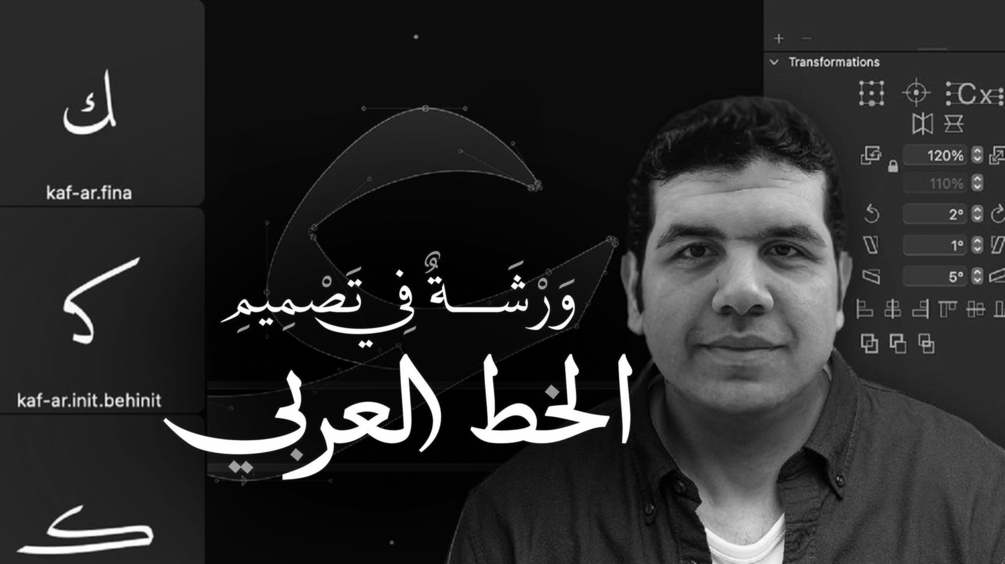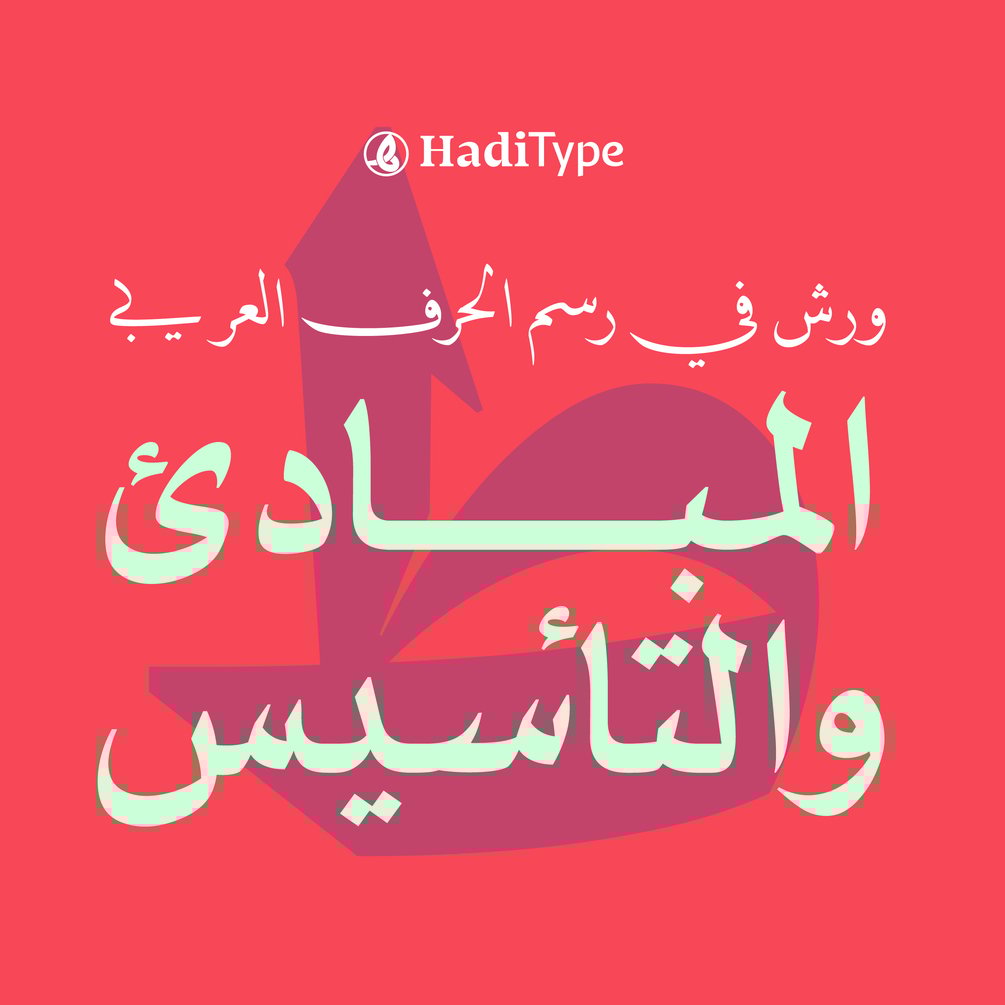
Arabic Type Design Course
هذا كورس مسجل من أخر دورة تمت تقديمها من كورس في رسم الحرف العربي ، وهو كورس تعليمي مختص في رسم وبرمجة الحرف الطباعي العربي، وهذا هو المستوى الأول المبادئ والتأسيس
مقدم هذا الكورس هو محمد هادي مؤسس
HadiType Foundry
الاستوديو المختص برسم وبرمجة الحروف الطباعية العربية ومقره القاهرة.
سوف نناقش هنا كيفية رسم خط طباعي كامل يعتمد على خط النسخ الحديث، مع شرح لبرنامج التصميم Glyphs App البرنامج الأشهر في صناعة الخطوط الرقمية.
محتويات كورس تصميم الخطوط الطباعية للمبتدئين
المبادئ والتأسيس.
المحاور الأساسية:-
● تشـــريح الحـــرف العـــــــربي.
● متطلبات رسم خط طباعي ناجح.
● أنواع واتجاهات الخطوط الطباعية العربية.
● التعرف على برنامج Glyphs وطرق رسم الحروف العربية.
● نظرية اعادة استخدام الاجزاء المتشابهة.
● ترابط وتوحيد نظام التصميم.
● رسم المفردات الأساسية  في اللغة العربية.
● اشتقاق المفردات الثانوية وضبط تموضع الحركات.
● رسم الأرقام الهندية.
● رسم وضبط الحركات.
● رسم المركبات ligatures
● الضبط الصحيح للفظ الجلالة الله
● استنتاج الاوزان.
● الفرق بين التباعدات والمسافات kerning & spacing
● شرح برمجة الاوبن تايب.
● إختبارات الخط.